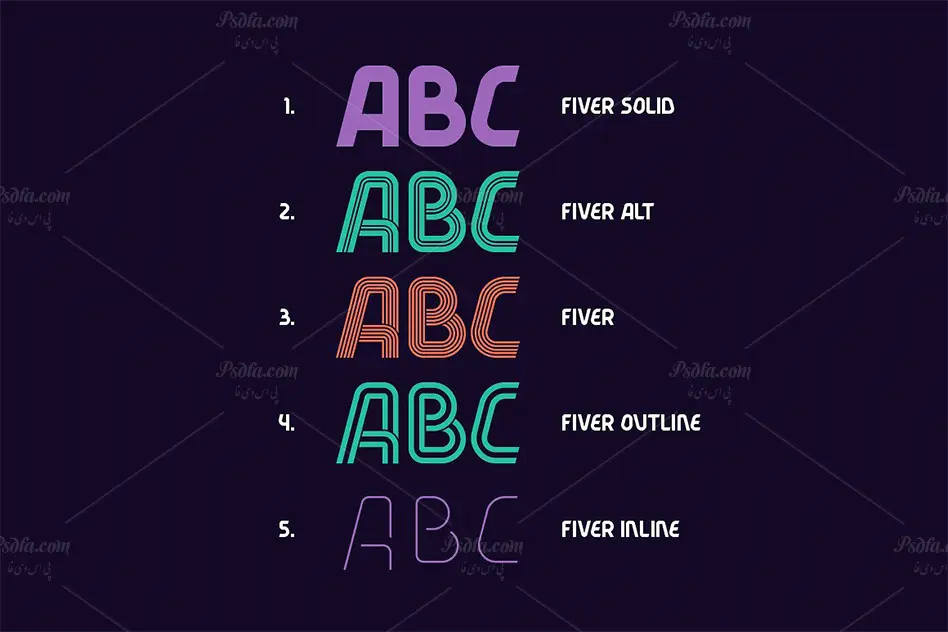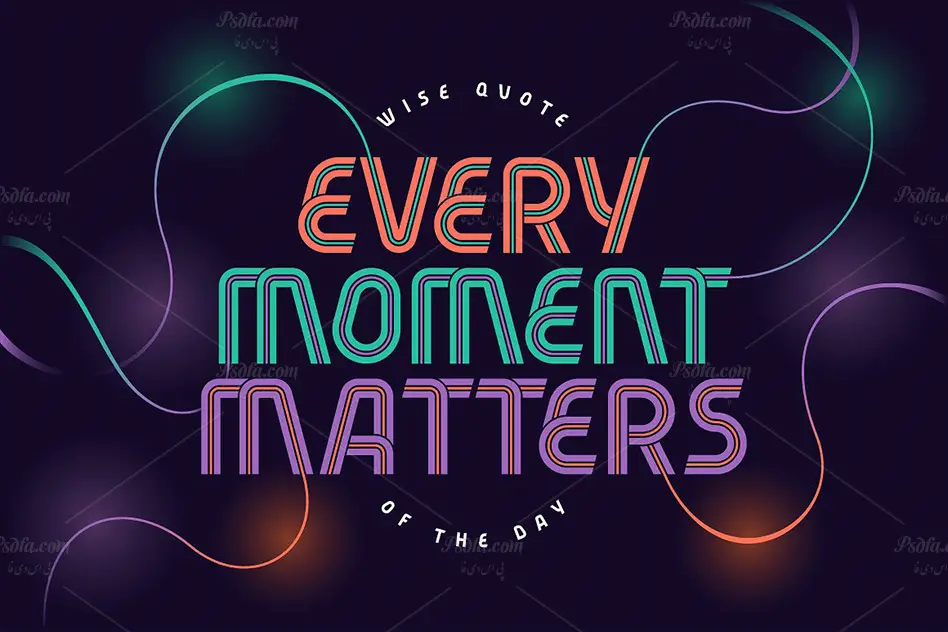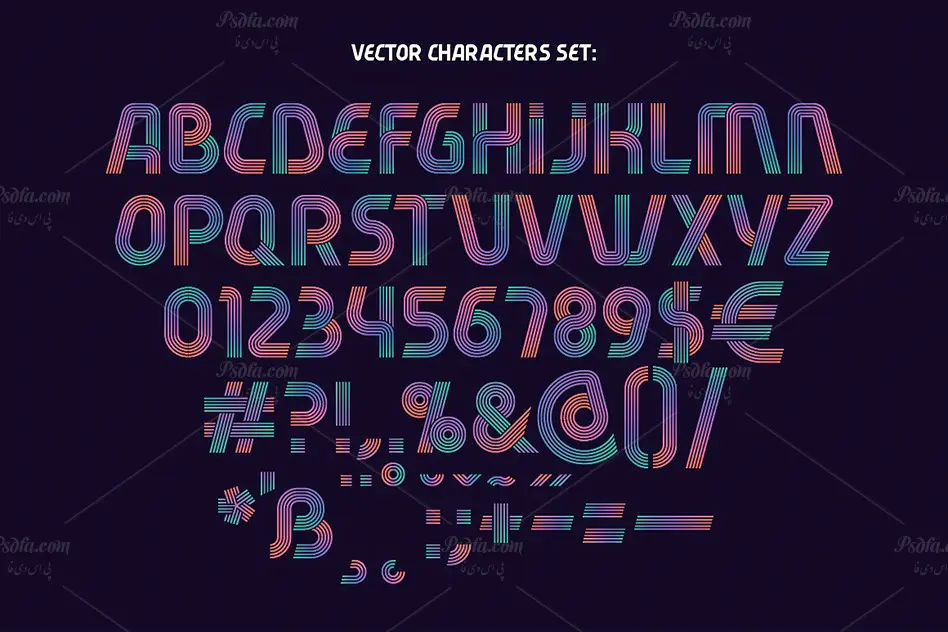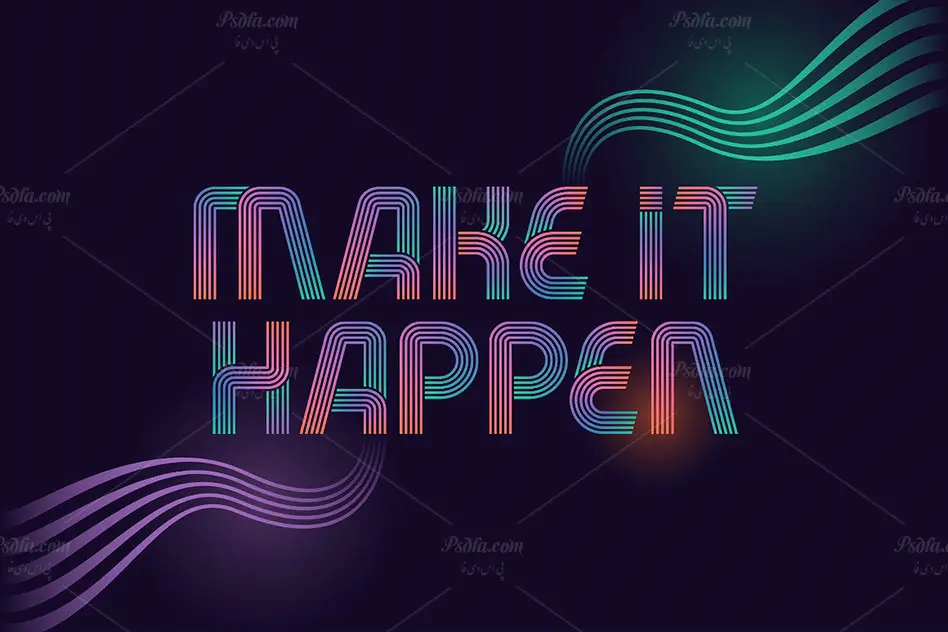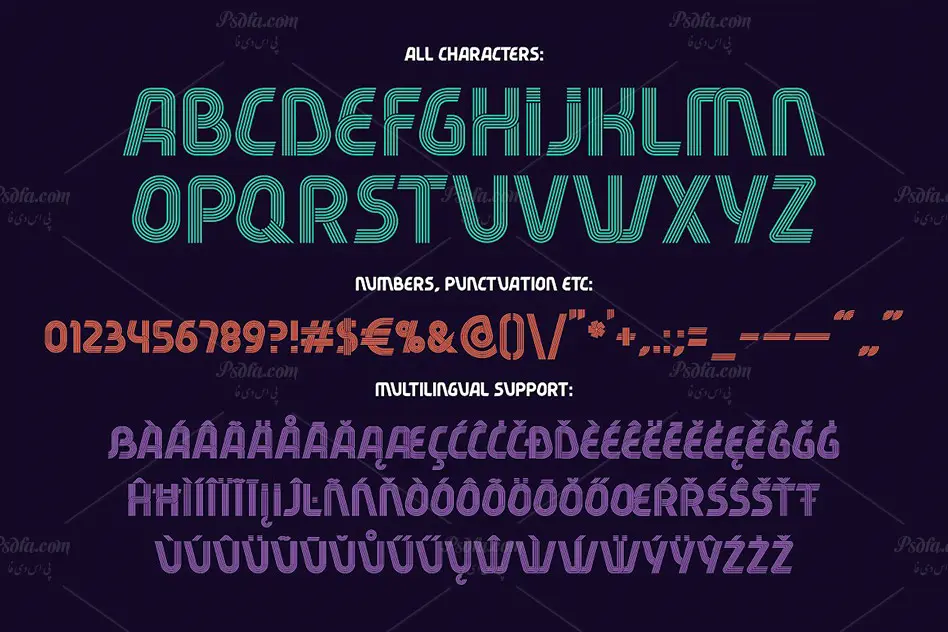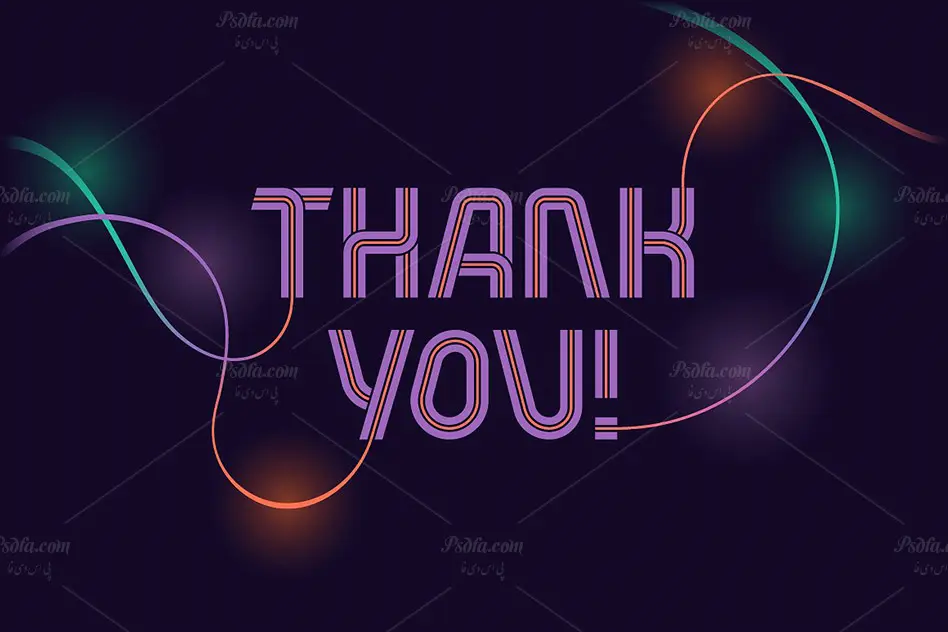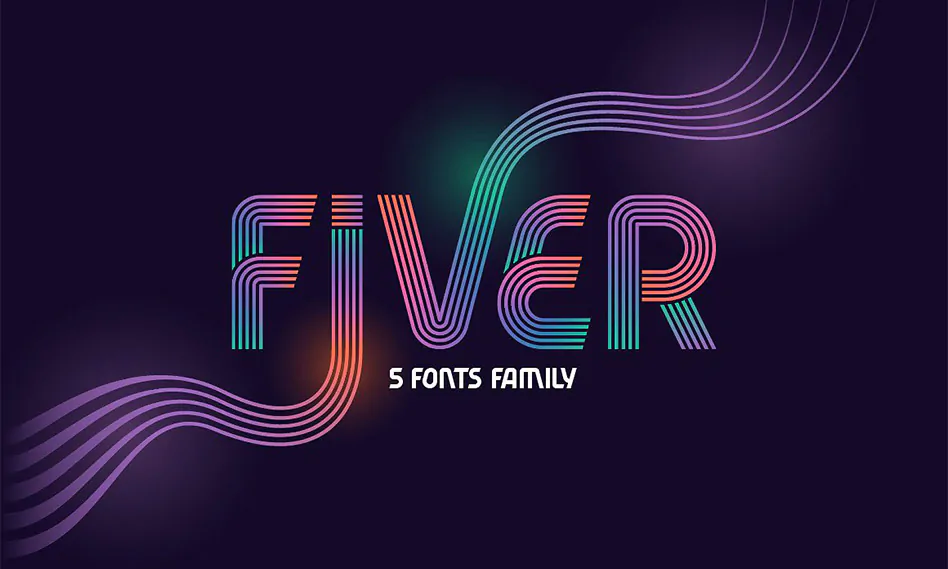
در این مطلب شاهد فونت انگلیسی راه راه Fiver مناسب جهت استفاده در طرح های گرافیکی به خصوص طراحی انواع پوستر می باشید. این فونت زیبا در قالب 5 فایل ttf و otf بر روی سایت بارگذاری شده اند که با نصب یکی از این دو فرمت در پوشه فونت های سیستم قادر به استفاده از آن ها در تمام نرم افزارهای گرافیکی و یا ویرایشگر متن از جمله نرم افزار فتوشاپ ، پریمیر ، افتر افکت ، مجموعه نرم افزار آفیس و … خواهید بود. فونت Fiver در 5 وزن توپر (Solid) ، خطی از داخل (Inline) ، خطی از بیرون (Outline) ، حروف بزرگ (Alt) و راه راه (Fiver) طراحی شده است که از آن ها می توان در طرح های گرافیکی همچون طراحی انواع پوستر ، بنر ، تراکت ، بروشور ، کارت تبریک ، کارت پستال و … استفاده نمود.
- نام فونت : Fiver
- وزن : Inline , Outline , Fiver , Alt , Solid